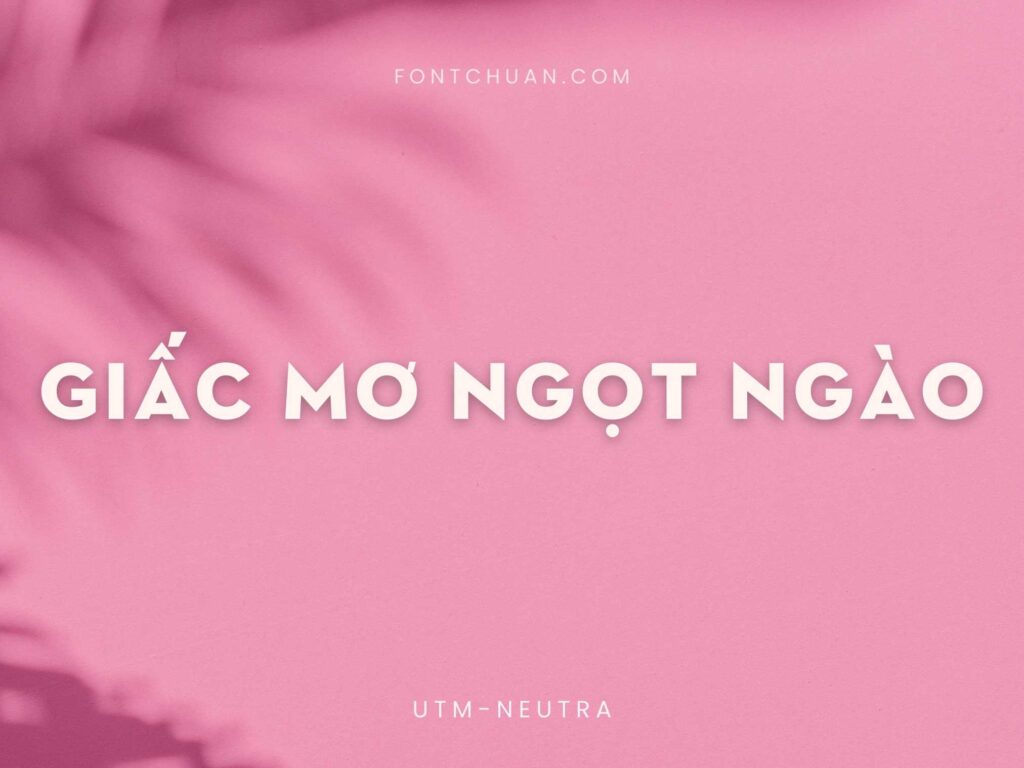
UTM Neutra là một font chữ sans-serif mang phong cách hiện đại và tối giản, được thiết kế để mang lại sự chuyên nghiệp và rõ ràng trong các thiết kế đồ họa. Font này có cấu trúc cân đối, hình dáng gọn gàng và dễ đọc, phù hợp với nhiều mục đích sử dụng khác nhau. Font đã được Việt hóa để hỗ trợ tiếng Việt, giúp mở rộng khả năng ứng dụng. Thành viên của Font Chuẩn đã sưu tầm và giới thiệu font này nhằm đáp ứng nhu cầu bạn đọc, cung cấp nguồn tham khảo chất lượng và ứng dụng thực tế vào các dự án thiết kế
Về đặc điểm thiết kế, UTM Neutra có các đường nét rõ ràng, độ dày đồng đều và kiểu dáng hiện đại. Font này phù hợp với nhiều ứng dụng như thiết kế thương hiệu, tài liệu chuyên nghiệp, website, trình bày văn bản, bảng hiệu và biển quảng cáo. Các ngành nghề như quảng cáo, giáo dục, công nghệ và thiết kế thương hiệu có thể tận dụng font này để tạo điểm nhấn và tăng tính chuyên nghiệp trong các sản phẩm thiết kế